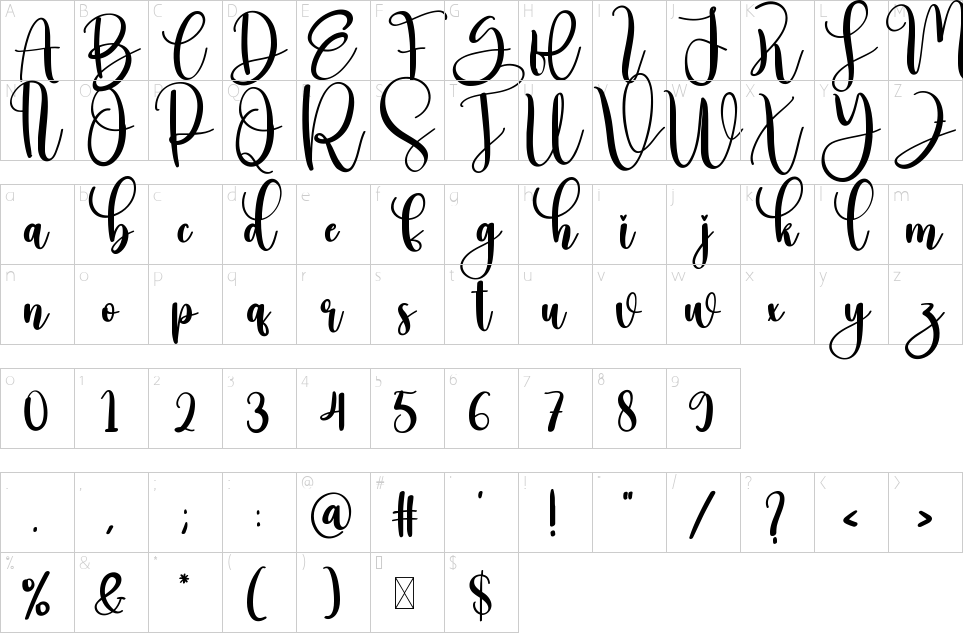
Esta fonte gratuita, chamada Anyone Font, é uma escolha ideal para quem busca uma fonte moderna e limpa para suas criações digitais. Ela foi criada por scratchones e já foi baixada 576 vezes, o que sugere que possui um design de bom gosto e versatilidade. Ideal tanto para designers gráficos quanto para profissionais de design web, esta fonte combina facilidade de uso com uma aparência atraente. Se você está procurando por uma opção de fontes sem custos para seu trabalho, Anyone Font é uma excelente escolha. Engajada e versátil, ela torna seu trabalho mais atraente sem a necessidade de gastar dinheiro.